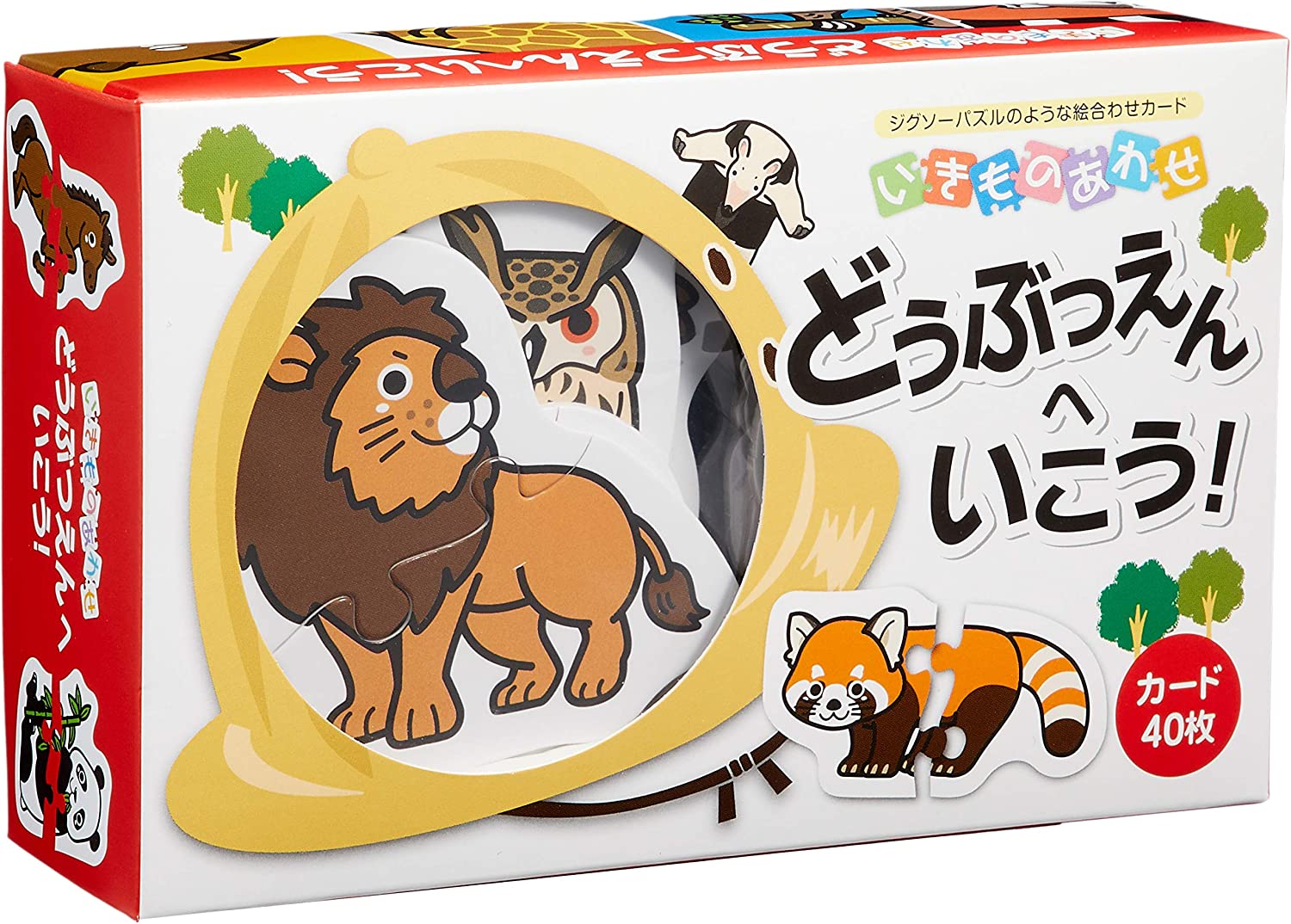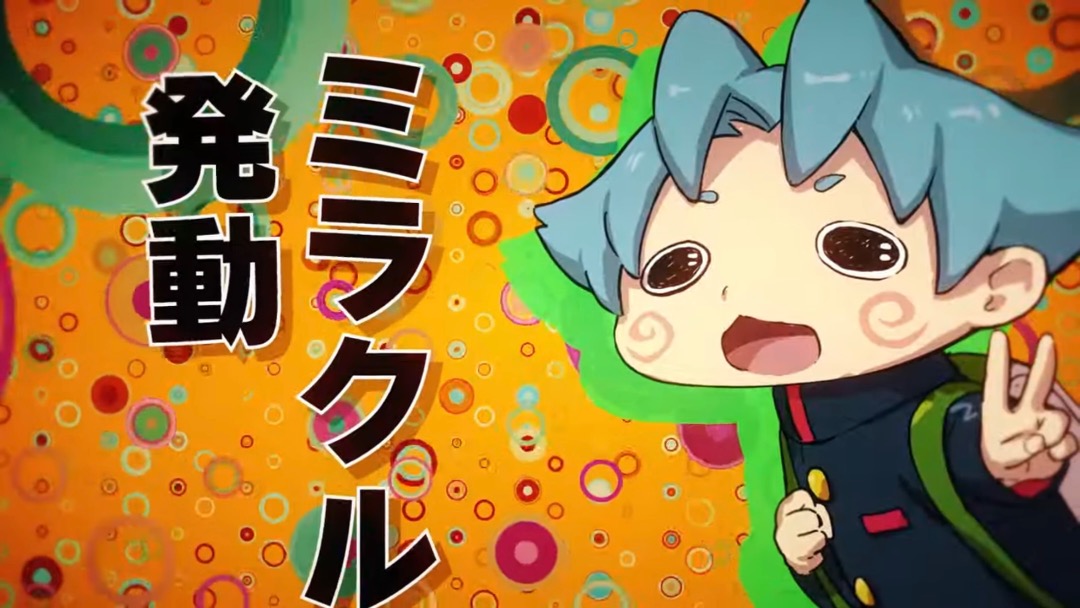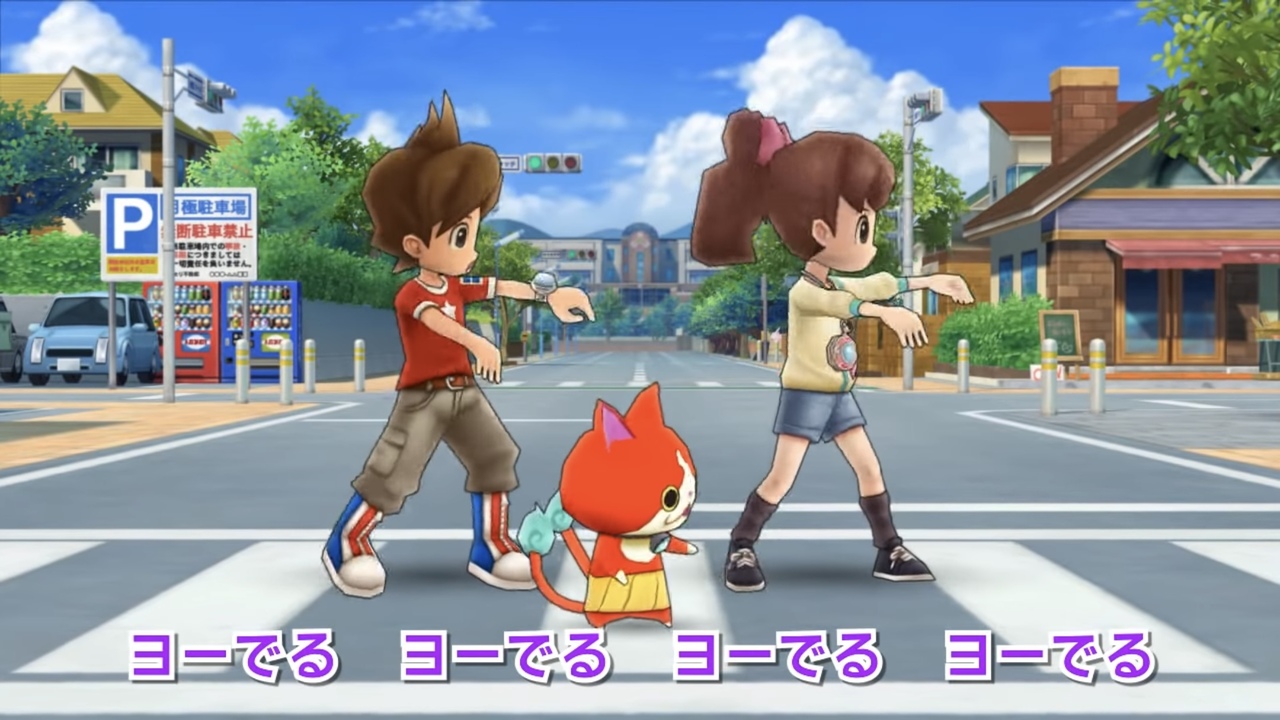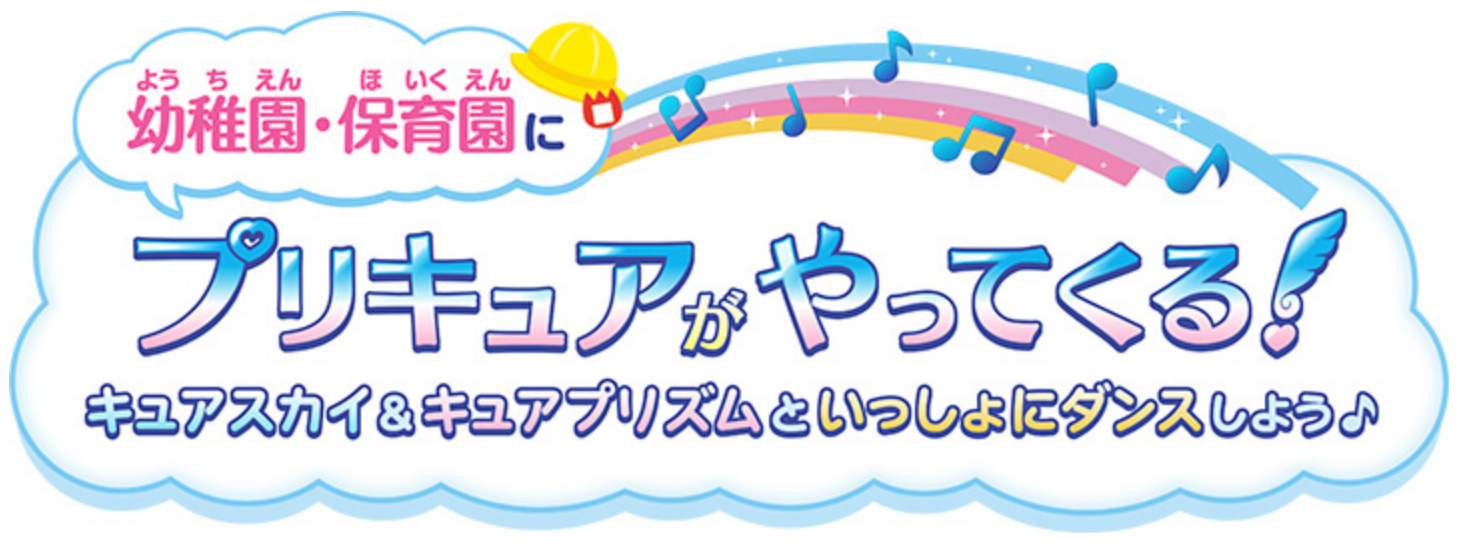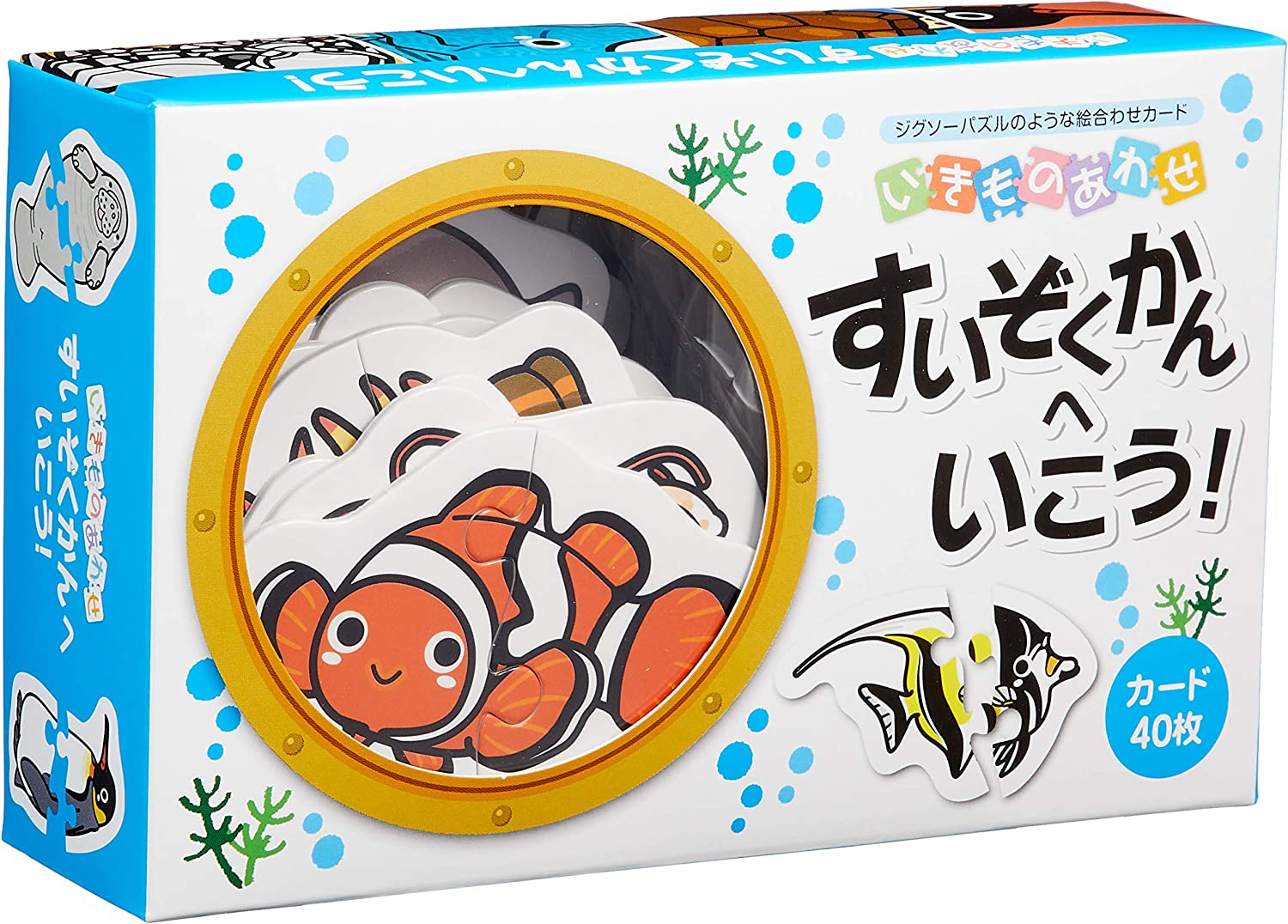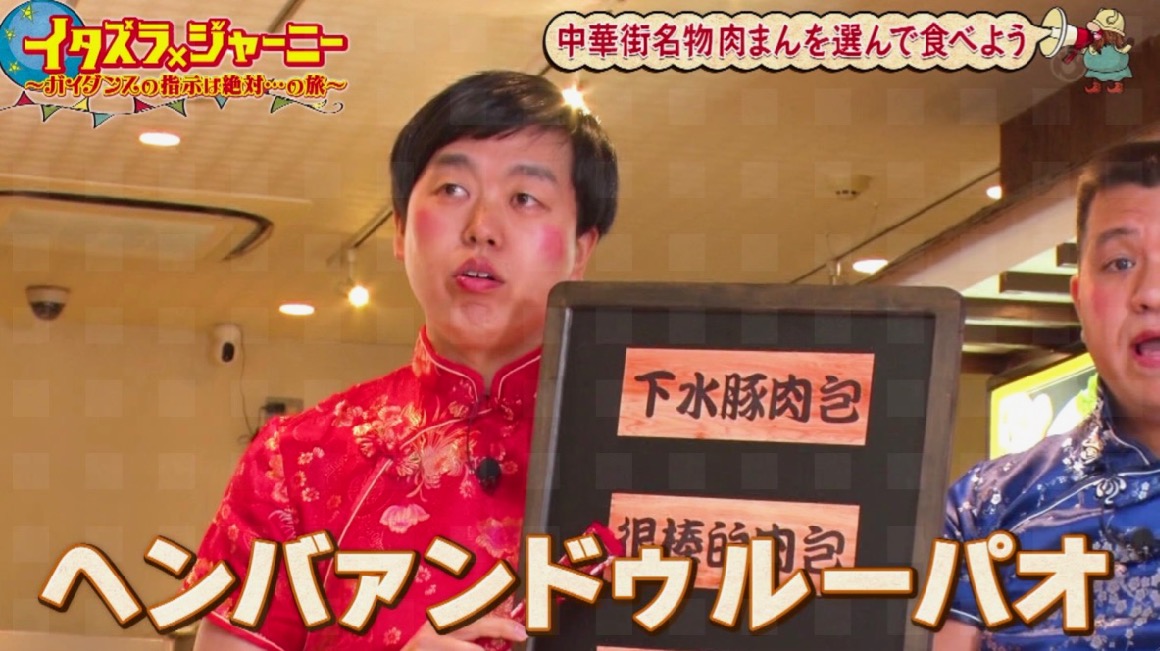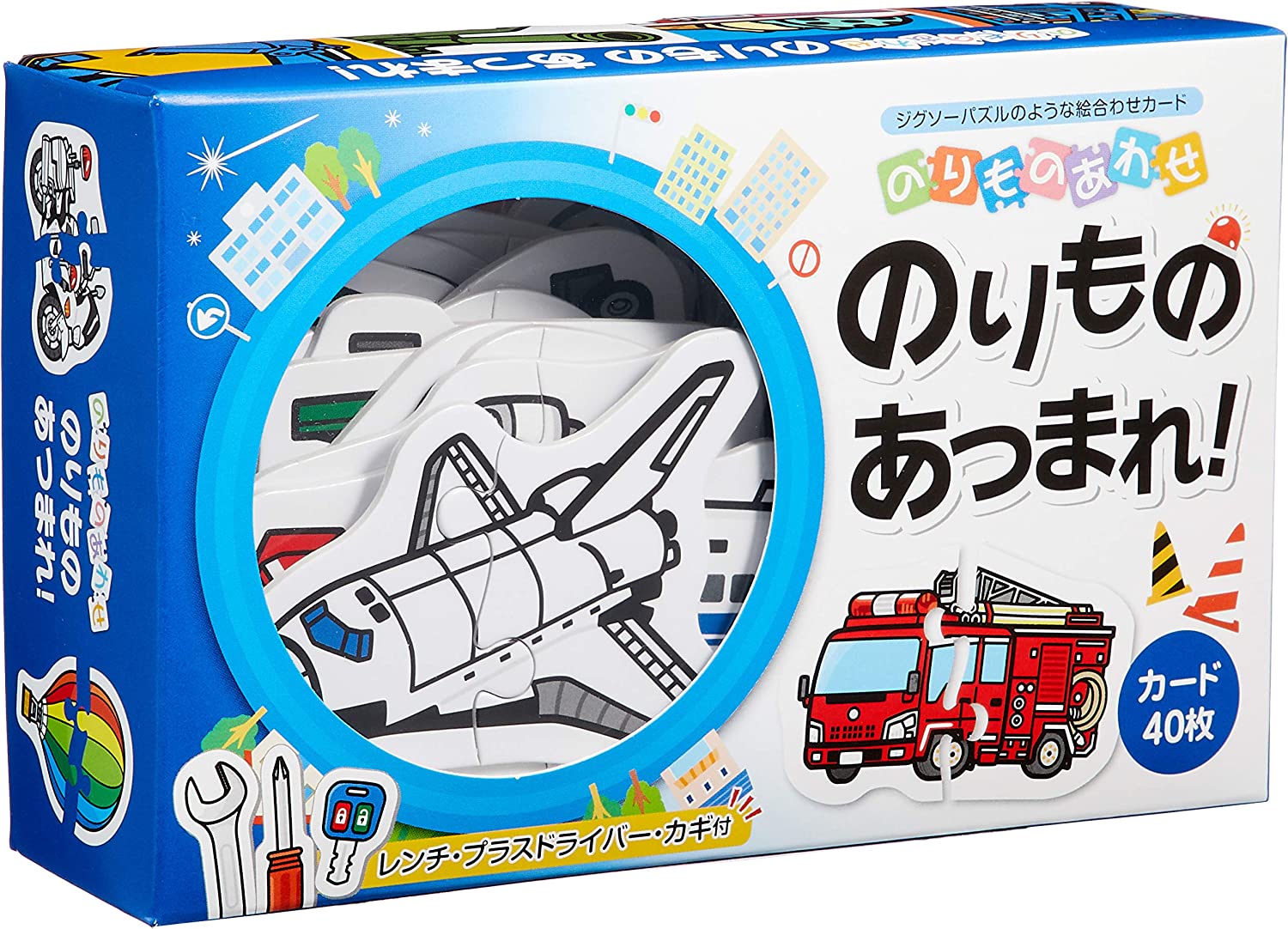
テレビ番組  さとうゆたか  2024年5月14日(火) 5:56
テレビ朝日「激レアさんを連れてきた。」
もうひとつ。
M社からのメール  takumi  2024年3月19日(火) 16:38  HP
サブスクの契約者向けに届いたメール。
「登録内容の変更に伴う〜」のかな部分がわんぱくフォントですね。
M社のわんぱくフォントが混植済みになったので、より使用例が増えるかも…。
混植済になったこと、まだ知らない人も多いんじゃないかな…。
本の表紙  さとうゆたか  2024年3月10日(日) 16:24
書名:初心者でも弾ける!はじめてのカリンバ・アンサンブルの本
発行:ケイ・エム・ピー
テレビ番組  さとうゆたか  2024年1月20日(土) 15:53
TBSテレビ、バナナマンのせっかくグルメ。
もうひとつ。
CDえほん  さとうゆたか  2024年1月2日(火) 9:27
書名:さるかに合戦・ねずみのすもう
著者:川内彩友美【編】
発行:講談社
同じシリーズ。
書名:きんたろう・てんぐの羽うちわ
著者:川内彩友美【編】
発行:講談社
書名:花さかじいさん・一休さん
著者:川内彩友美【編】
発行:講談社
まだある…。
書名:うらしまたろう・きき耳ずきん
著者:川内彩友美【編】
発行:講談社
もうひとつ。
書名:いっすんぼうし・わらしべ長者
著者:川内彩友美【編】
発行:講談社
スーパーのPOP  takumi  2023年12月25日(月) 22:28  HP
スーパーのPOPで使われていた「わんぱく」フォントです。
あ    さとうゆたか  2023年12月3日(日) 11:20
書名:ぼくのまちをつくろう!
著者:杉山佳奈代
発行:理論社
番組タイトル  さとうゆたか  2023年11月16日(木) 20:43
テレビ埼玉の番組。
ダイソーの商品  takumi  2023年11月12日(日) 16:03  HP
ダイソーの商品の台紙です。
左の黄色い吹き出しに「わんぱくレラ」が使われています。
右の「推し撮り」の「し」と「り」はえれがんとですね。
テレビ番組  さとうゆたか  2023年10月16日(月) 11:26
日本テレビ「スクール革命」。